Nếu bạn đang tìm cách làm cho văn bản tiếng Nhật trên máy tính trở nên sinh động và cuốn hút hơn, thì việc tải font tiếng Nhật đẹp chính là bước đầu tiên không thể bỏ qua. Những font chữ này không chỉ giúp hiển thị rõ nét các ký tự Kanji, Hiragana, Katakana mà còn mang lại tính thẩm mỹ cao cho thiết kế, tài liệu hoặc bài thuyết trình. Bài viết này, Vietkey sẽ giới thiệu đến bạn những font tiếng Nhật phổ biến và hướng dẫn chi tiết cách cài đặt, giúp bạn dễ dàng sử dụng trên mọi thiết bị.
Font tiếng Nhật là gì?
Tiếng Nhật ngày nay đã trở nên quen thuộc trên toàn thế giới với hệ thống chữ viết độc đáo và tinh tế. Khác với bảng chữ cái Latinh thông thường, chữ viết tiếng Nhật được cấu thành từ ba hệ chữ chính gồm Hiragana, Katakana và Kanji (chữ Hán). Mỗi hệ chữ mang một vai trò và phong cách riêng, thể hiện nét đẹp văn hóa đặc trưng của đất nước mặt trời mọc.
Để có thể hiển thị và soạn thảo tiếng Nhật một cách chuẩn xác, việc lựa chọn font tiếng Nhật phù hợp là vô cùng quan trọng. Những bộ font này không chỉ hỗ trợ việc học tập và nghiên cứu ngôn ngữ mà còn được ứng dụng rộng rãi trong thiết kế, trình bày tài liệu và các sản phẩm sáng tạo khác.
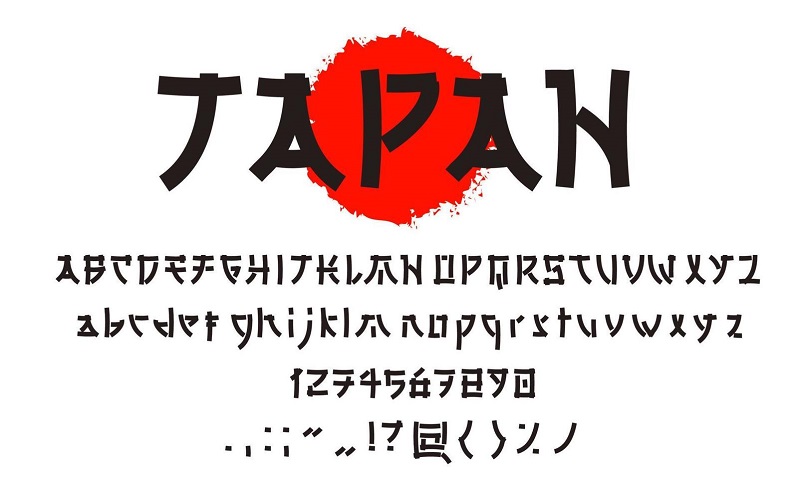
Tổng hợp 12 font tiếng Nhật đẹp và được dùng phổ biến
Tải font tiếng Nhật đẹp không chỉ giúp hiển thị văn bản rõ ràng hơn mà còn mang đến cảm hứng sáng tạo khi làm việc với ngôn ngữ này. Dưới đây là tổng hợp 12 font tiếng Nhật được yêu thích và sử dụng phổ biến nhất hiện nay:
Font chữ Ms Mincho
Ms Mincho là một trong những font chữ tiếng Nhật đẹp được cài đặt sẵn trên hầu hết các hệ điều hành Windows. Kiểu chữ này mang phong cách truyền thống, các nét thanh đậm rõ ràng, tạo cảm giác trang nhã và dễ đọc. Nhờ thiết kế đơn giản và cân đối, Ms Mincho thường được sử dụng trong các văn bản dài như luận văn, báo cáo, hay tài liệu nghiên cứu, giúp người đọc dễ dàng theo dõi và tập trung vào nội dung.
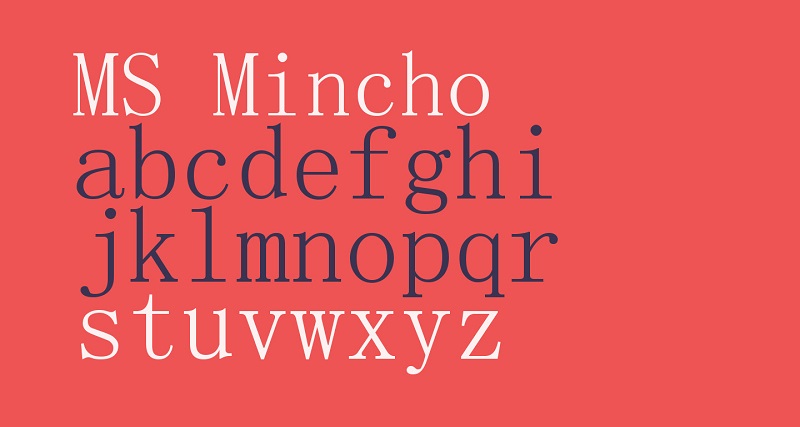
Font chữ Epson
Epson là bộ font tiếng Nhật miễn phí được phát triển bởi tập đoàn sản xuất máy in nổi tiếng Epson. Với thiết kế tinh gọn và hài hòa, font chữ này được sử dụng phổ biến tại Nhật Bản trong nhiều loại tài liệu khác nhau. Nhờ tính linh hoạt cao, người dùng có thể áp dụng Epson font cho các văn bản mang tính trang trọng, cũng như trong các ấn phẩm thương mại, quảng cáo hoặc thiết kế đồ họa chuyên nghiệp.
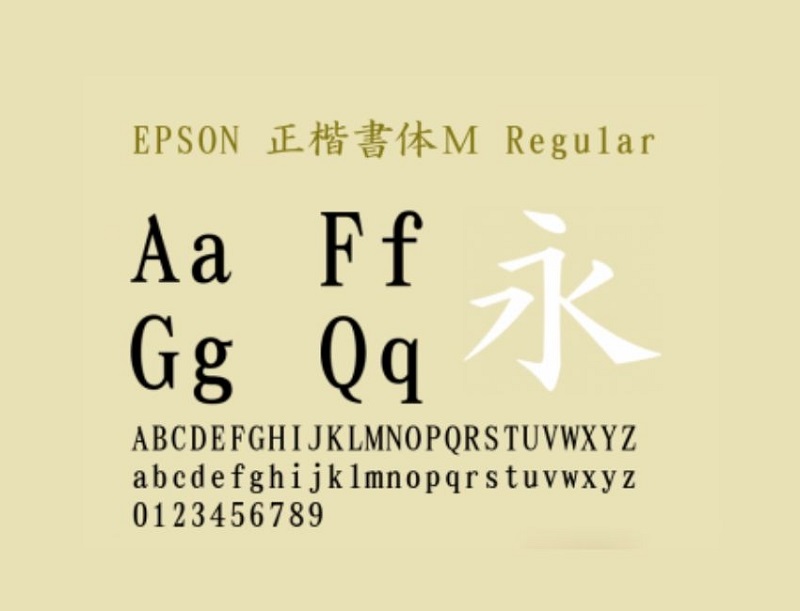
Font chữ Hanazono
Được nhiều người dùng đánh giá cao nhờ vẻ đẹp tinh tế và nhẹ nhàng, font Hanazono mang đến cảm giác dễ chịu khi đọc và hiển thị. Bộ font này hỗ trợ chuẩn Unicode, giúp tương thích tốt với nhiều ngôn ngữ và ký tự khác nhau. Hanazono bao gồm đầy đủ các dạng chữ của tiếng Nhật, từ nét mềm mại của Hiragana, sự cứng cáp của Katakana cho đến những ký tự Kanji phức tạp, phù hợp cho cả học tập lẫn trình bày chuyên nghiệp.
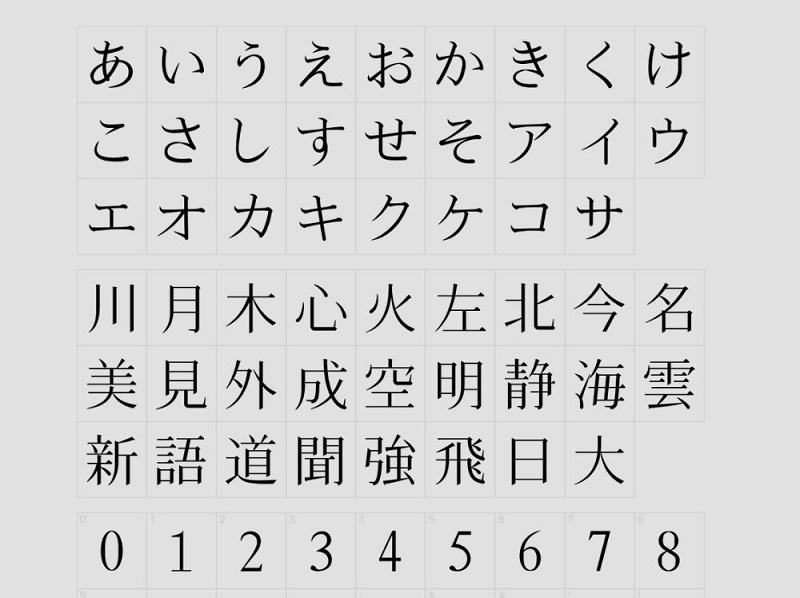
Font chữ Hkgokukaikk
Font Hkgokukaikk gây ấn tượng với kiểu chữ dày và đậm, mang lại cảm giác mạnh mẽ và chắc chắn khi hiển thị. Nhờ đặc điểm dễ nhìn và rõ nét, font này giúp người đọc dễ dàng nhận diện từng ký tự. Hkgokukaikk thường được sử dụng cho phần chữ Furigana, bao gồm các ký tự Hiragana và Katakana dùng để chú thích, phiên âm cho chữ Kanji, hỗ trợ hiệu quả trong việc học và đọc tiếng Nhật.
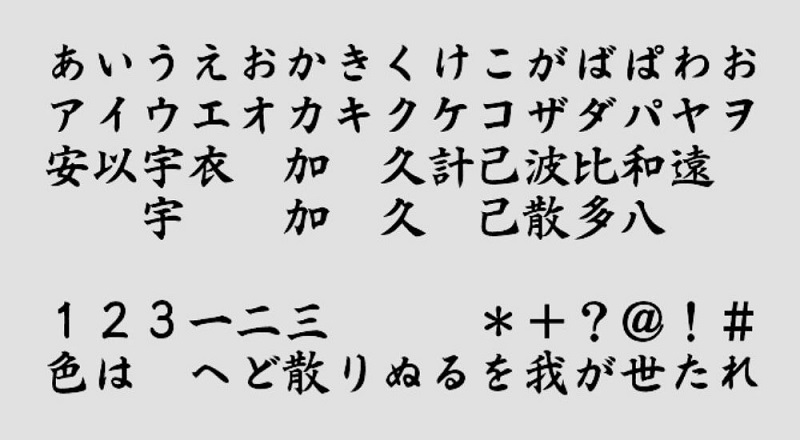
Font chữ Hkgyong
Đối với những ai yêu thích phong cách thư pháp truyền thống, Hkgyong là lựa chọn lý tưởng khi muốn tải font tiếng Nhật đẹp để sử dụng trong thiết kế hoặc trình bày văn bản. Font này nổi bật với các đường nét mềm mại, uyển chuyển và tinh tế, tạo cảm giác cổ điển nhưng vẫn giữ được vẻ sang trọng, phù hợp cho những dự án mang hơi hướng nghệ thuật hoặc văn hóa Nhật Bản.
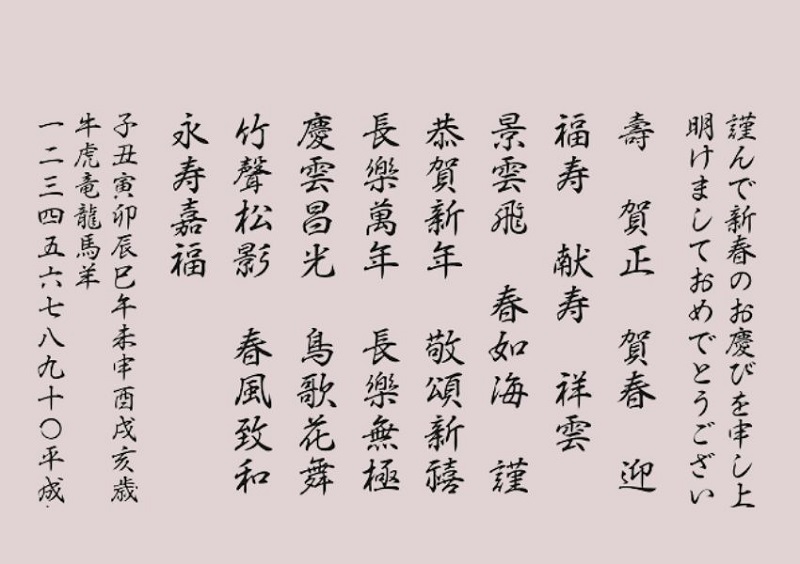
Font chữ Hkkaiiw
Nếu bạn muốn tải font tiếng Nhật đẹp để dùng cho các thiết kế mang tính thẩm mỹ cao, Hkkaiiw là lựa chọn đáng cân nhắc. Font này thường được sử dụng trong việc viết thiệp chúc mừng, trang trí ấn phẩm hay các thiết kế nghệ thuật nhờ vào nét chữ thanh thoát, tinh tế. Với đường nét rõ ràng và bố cục cân đối, Hkkaiiw mang đến cảm giác sang trọng, nhã nhặn và thu hút ngay từ cái nhìn đầu tiên.
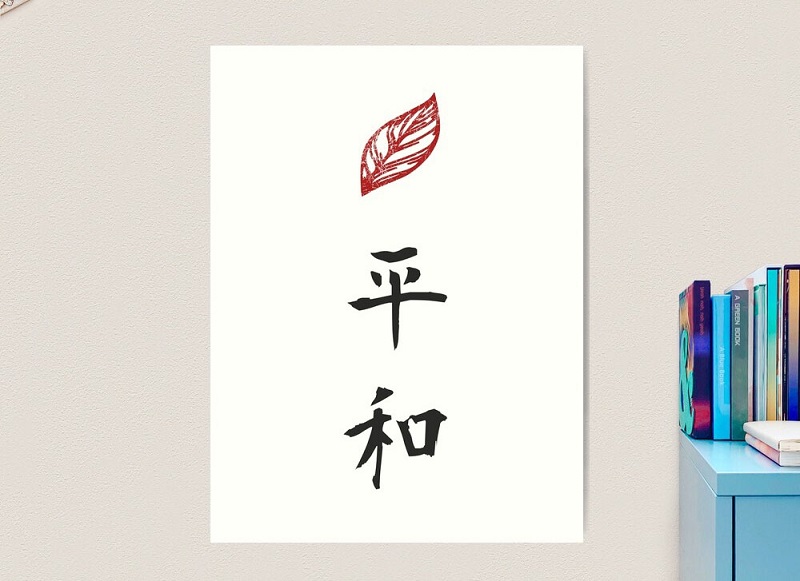
Font chữ Hksoung
Thuộc nhóm font thư pháp được yêu thích, Hksoung mang phong cách viết tay nhanh và tự nhiên, gợi cảm giác như những nét bút viết liền mạch trên giấy. Kiểu chữ này được lấy cảm hứng từ cách viết tắt, viết láu trong tiếng Nhật, thể hiện sự phóng khoáng và nghệ thuật. Tuy nhiên, do các nét chữ nối liền và biến hóa tinh tế, người đọc cần có hiểu biết nhất định về tiếng Nhật mới có thể nhận diện và đọc chính xác nội dung.
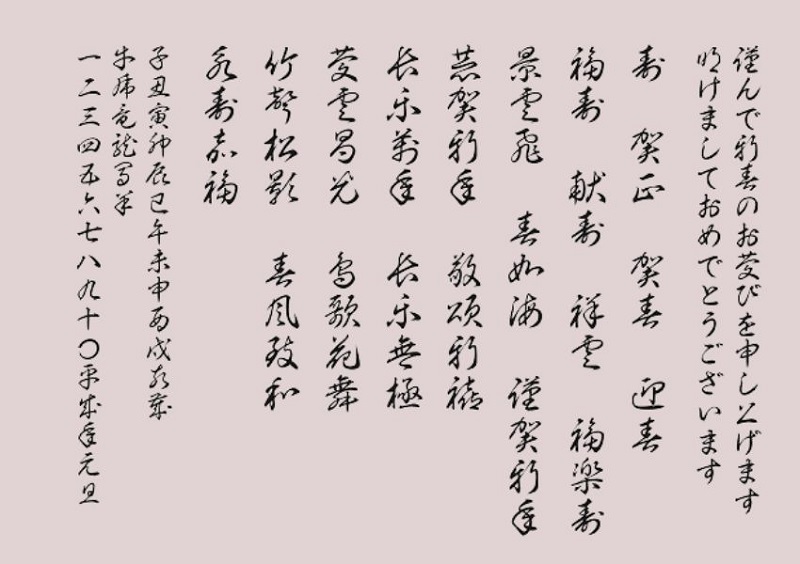
Font chữ Honoka Marugo
Với thiết kế tròn trịa và các nét chữ mềm mại, Honoka Marugo mang đến cảm giác dễ chịu và thân thiện khi hiển thị trên màn hình. Nhờ khả năng giữ độ rõ ràng ngay cả ở kích thước nhỏ, font này giúp văn bản trở nên dễ đọc và cân đối hơn. Honoka Marugo thường được sử dụng trong nhiều mục đích khác nhau như thiết kế đồ họa, ấn phẩm quảng cáo hoặc tài liệu học tập, mang lại cảm giác ấm áp và gần gũi cho người xem.